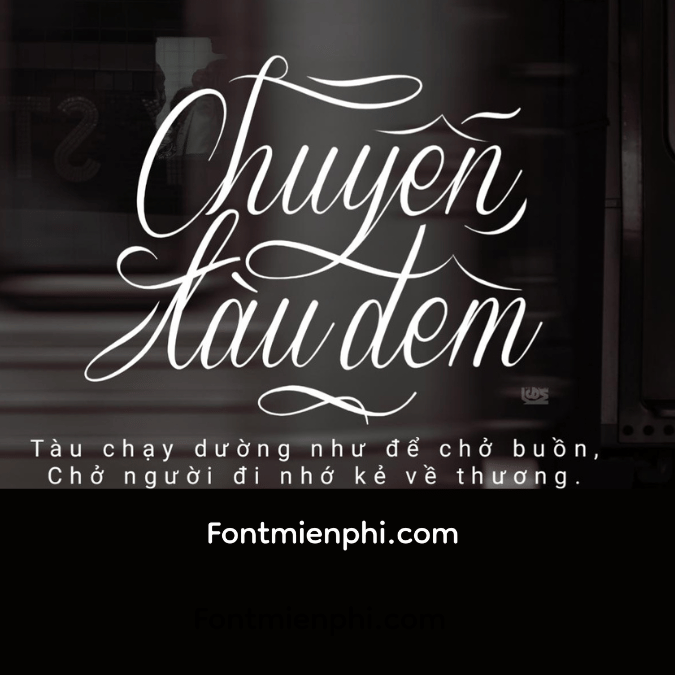
FONT VIỆT HÓA 1FTV VIP SVERIGE SCRIPT
“Dòng chữ Bắc Âu – Tinh tế từng nét cong”
ĐẶC ĐIỂM NỔI BẬT
❄️ Phong cách Scandinavian Minimalist: Nét chữ lấy cảm hứng từ thiết kế Bắc Âu với độ dày biến đổi tinh tế
️ Chất calligraphy hiện đại: Kết hợp nét thanh-đậm tự nhiên như viết tay, nhưng vẫn giữ sự rõ ràng
Họa tiết thiên nhiên: Điểm xuyến các nét phụ cách điệu từ lá thông, tuyết rơi
ỨNG DỤNG CAO CẤP
• Nhận diện thương hiệu Eco/Food
• Bao bì sản phẩm hữu cơ, đồ gốm handmade
• Thiệp mời tiệc mùa đông, Christmas
• Menu nhà hàng phong cách Nordic
BỘ VIP ĐẶC BIỆT
3 phiên bản độc quyền:
• Regular (nét chuẩn)
• Snow (hiệu ứng tuyết rơi)
• Linen (texture vải lanh)
“Sverige Script – Hơi thở Bắc Âu trong từng con chữ”
GỢI Ý THIẾT KẾ
• Màu chủ đạo: Xanh pine #01796F + Trắng tuyết #F8F8FF
• Chất liệu: Giấy kraft, gỗ sồi tự nhiên
• Hiệu ứng: Bóng đổ mờ 3D nhẹ